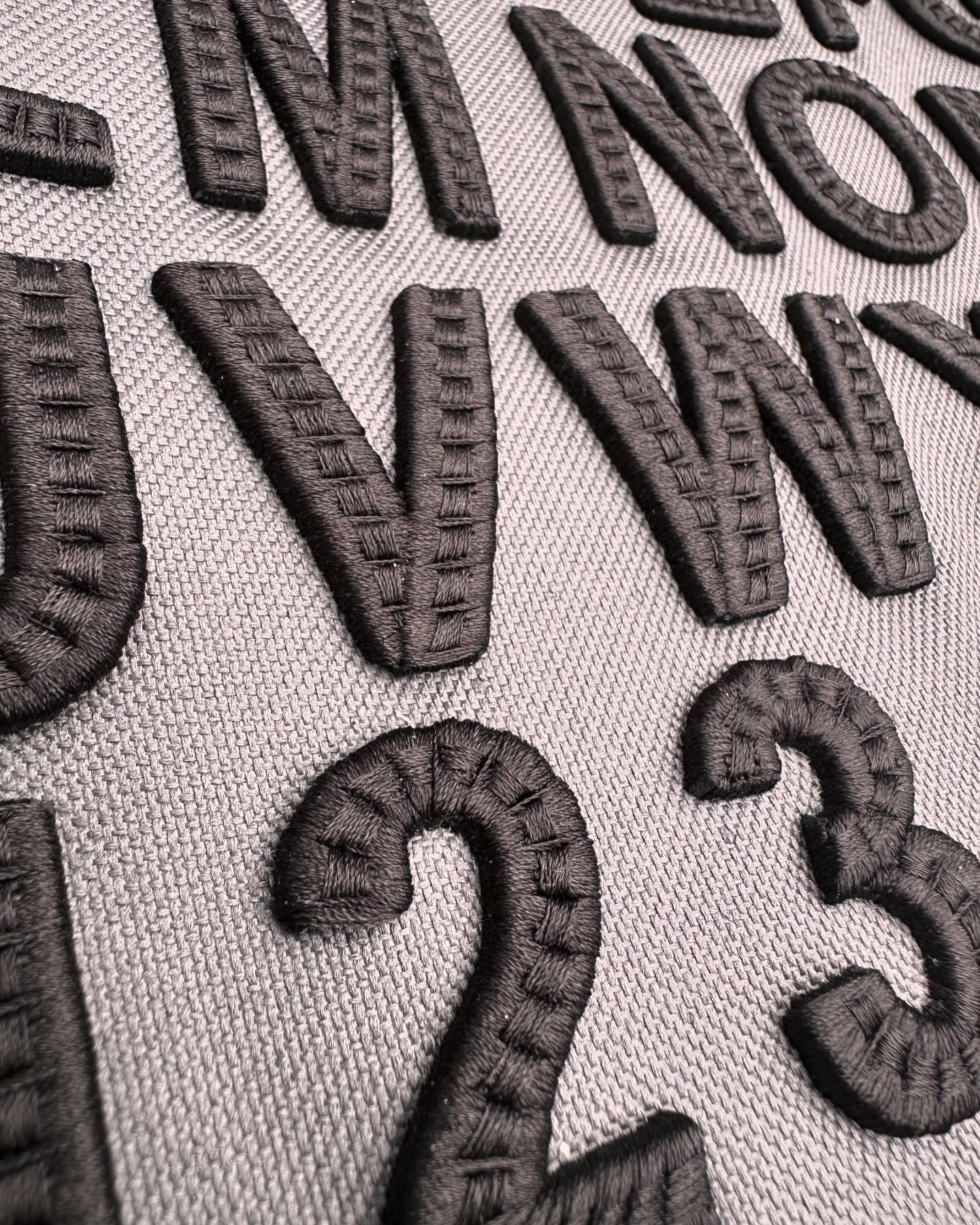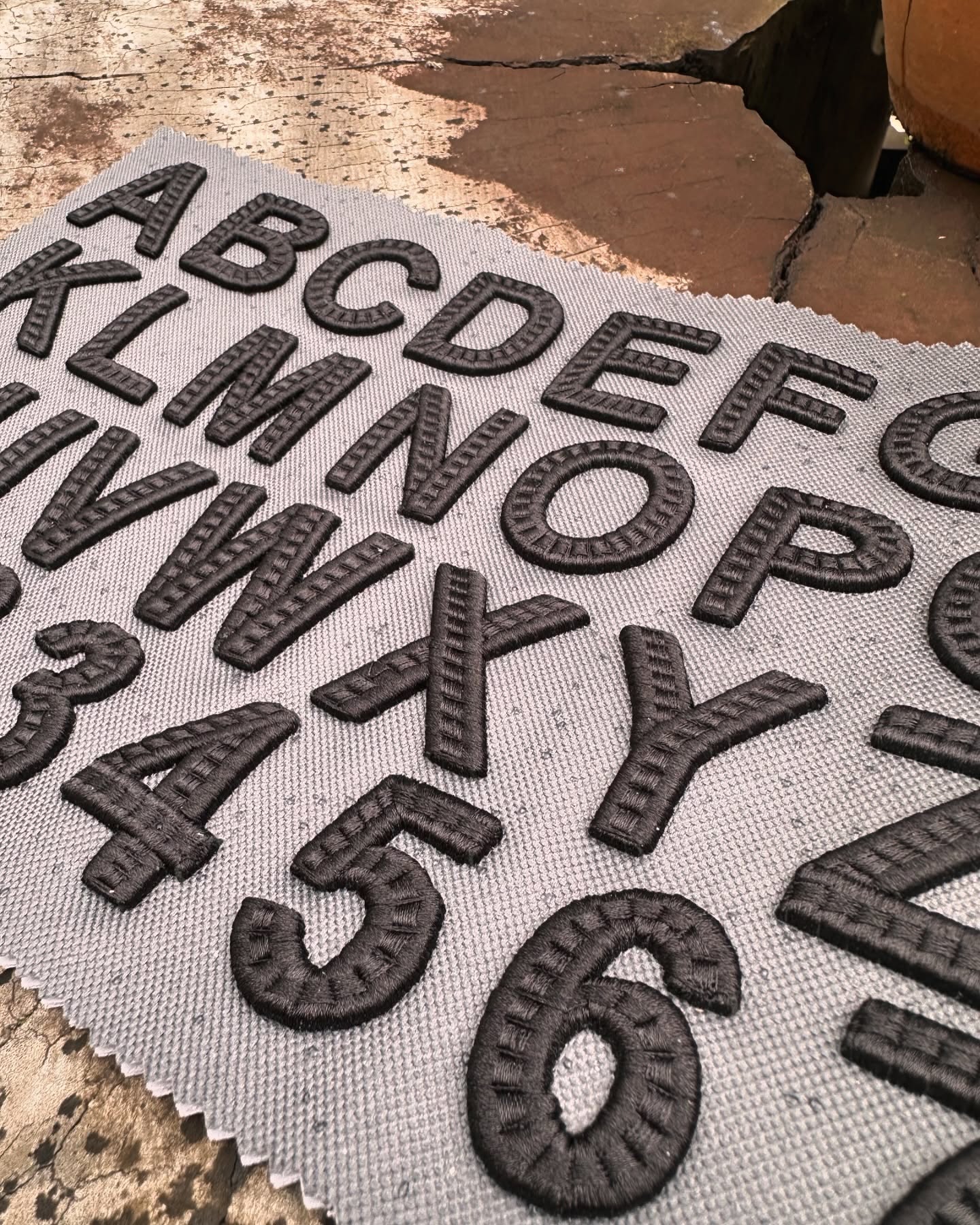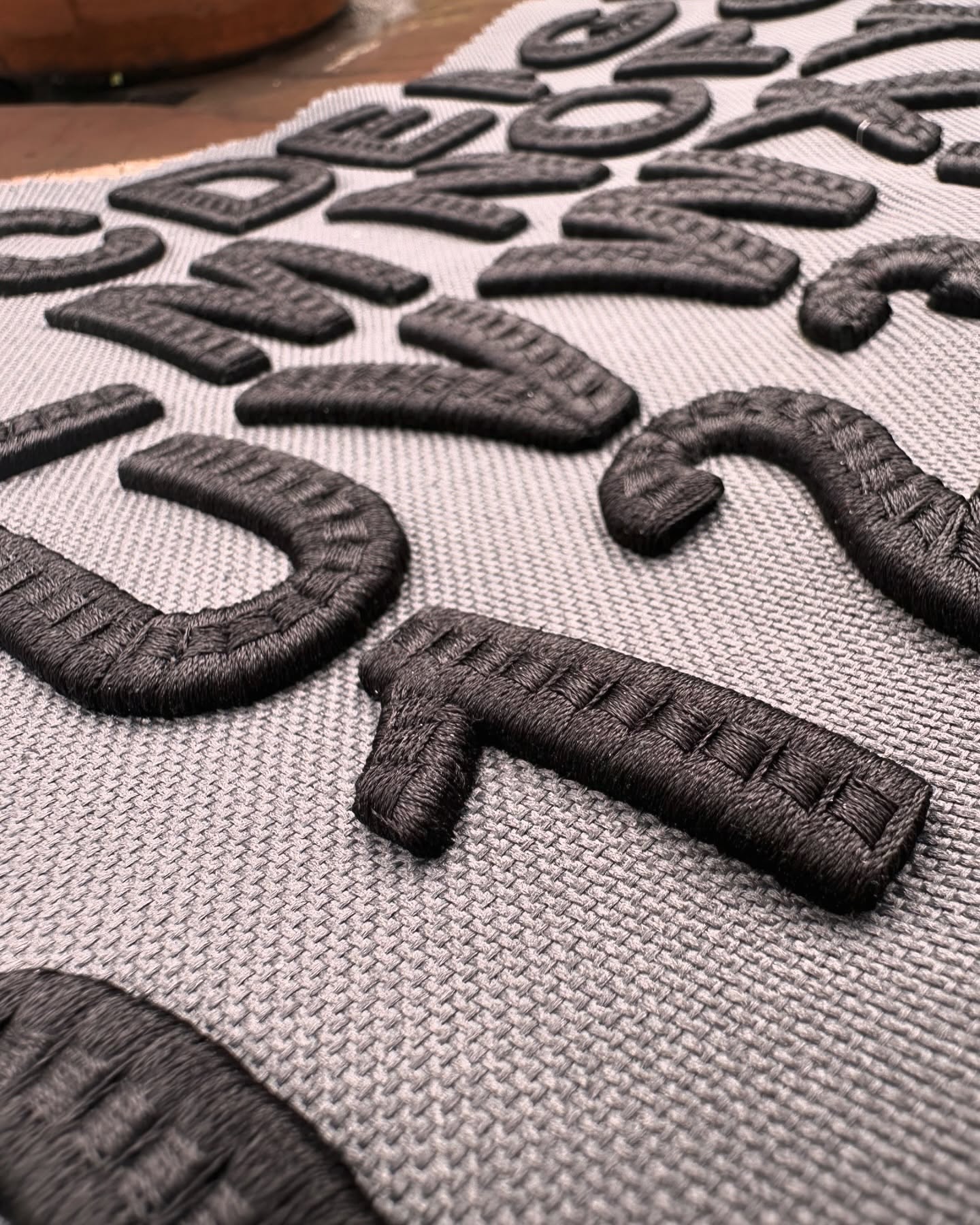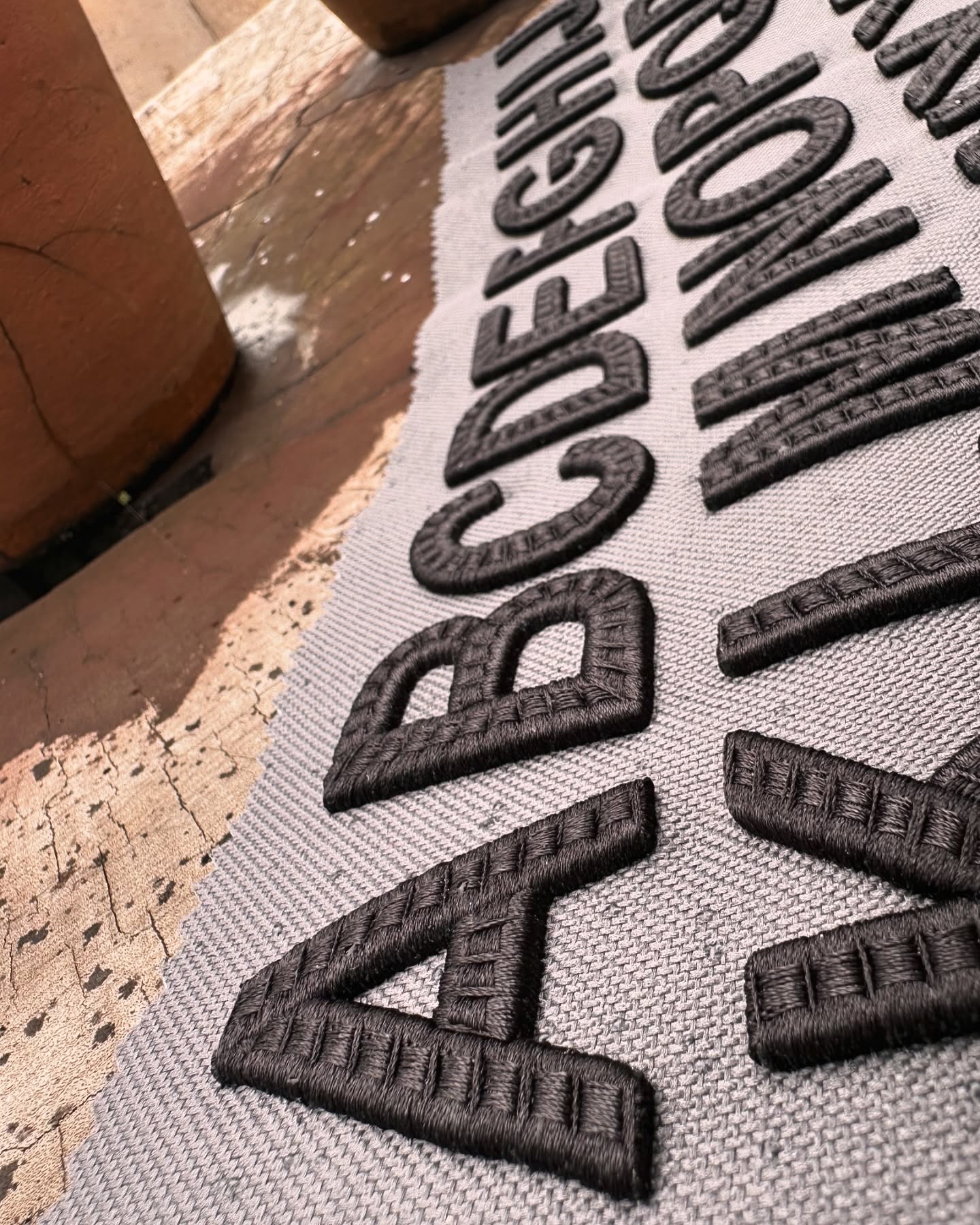
جريء ومرتفع: مجموعة خطوط التطريز ثلاثية الأبعاد Puff CrossCenter Chain Stitch - أحرف كبيرة وأرقام
ارفع مستوى التطريز الخاص بك مع جريئة ومرتفعة ، مجموعة حيث نفخة ثلاثية الأبعاد يلتقي غرزة السلسلة CrossCenter للحصول على ملمس وأبعاد لا مثيل لها.
يتميز كل حرف كبير ورقم بتقنية هجينة فريدة: حيث تخلق الطبقة السفلية من الرغوة المرتفعة حجمًا ثلاثي الأبعاد جريئًا، بينما تتقاطع غرزة السلسلة الدقيقة عبر المركز، مما يضيف تفاصيل معقدة وسحرًا عتيقًا.
مثالية للشعارات أو قمصان الفريق أو المعدات المخصصة، تجمع مجموعة الخطوط هذه بين المتانة والتأثير البصري المذهل.
الدراما الأبعادية: رغوة نفخ ثلاثية الأبعاد تعطي الحروف/الأرقام رفع ملموس وجذاب للنظر مثالية للعلامات التجارية البارزة.
تفاصيل CrossCenter: تضيف الخياطة المتسلسلة عبر مركز كل حرف عمقًا وإشارة إلى الحرفية العتيقة.
صُممت لتدوم: خياطة معززة على القبعات، تضمن أن تتحمل التصميمات الاستخدام اليومي.